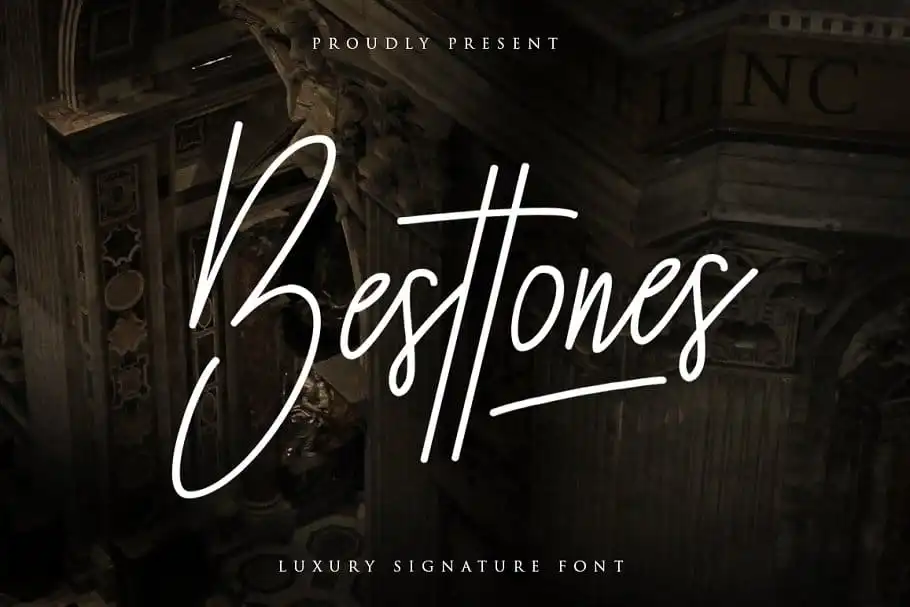
A fonte ‘Besttones Signature Font’ é uma escolha inovadora para designers que valorizam a simplicidade e a sofisticação ao mesmo tempo. Esta elegante fonte cursiva foi criada pelo designer Hamilton, inspirada nas marcas de assinatura e em estilos modernos e icônicos. Perfeita tanto para ambientes profissionais como pessoais, ela se destaca especialmente para projetos como logotipos e identidade visual, convites e embalagens de papelaria, desenho de casamentos, postagem nas redes sociais, anúncios publicitários, embalagens de produtos, etiquetas, fotografia e até mesmo rótulos. A fonte ‘Besttones Signature Font’ é um atalho para incorporar elegância e modernidade em qualquer projeto visual. Inspirada no gosto pessoal do designer Hamilton, esta fonte se torna o instrumento ideal que você precisa para dar um toque único aos seus projetos de design gráfico.